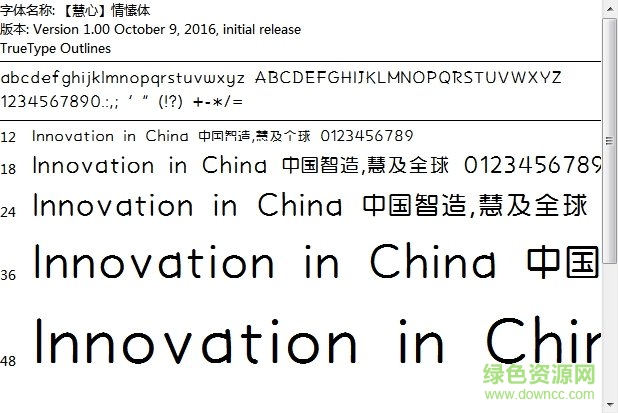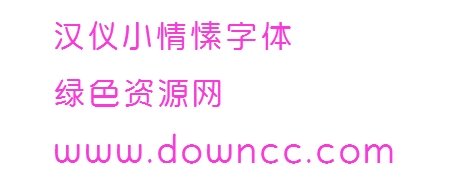
漢儀小情愫字體
漢儀小情愫ttf是漢儀字庫推出的一款中文字體,不同于常見的微軟雅黑和宋體,本字體在結(jié)構(gòu)上更加獨(dú)特,造型大方閱讀清晰,藝術(shù)效果十分不錯(cuò),來綠色資源網(wǎng)下載,相信你也會(huì)很喜歡它的!
漢儀小情愫字體介紹
情愫代表在特定情境下的一種只可意會(huì)不可言傳的心境。類似于日久生情,一般指長久的相處中漸生好感。暗藏于心。
漢儀小情愫
漢儀小情愫字體特色
漢儀小情愫即慧心青素體,常見于oppo手機(jī)上,字體結(jié)構(gòu)形散神不散,給人稀疏簡潔的書法美感,常規(guī)造型中又有著自己的特色魅力,給人極佳的視覺體驗(yàn),可以使用在廣告創(chuàng)意、海報(bào)設(shè)計(jì)、排版印刷等場合。